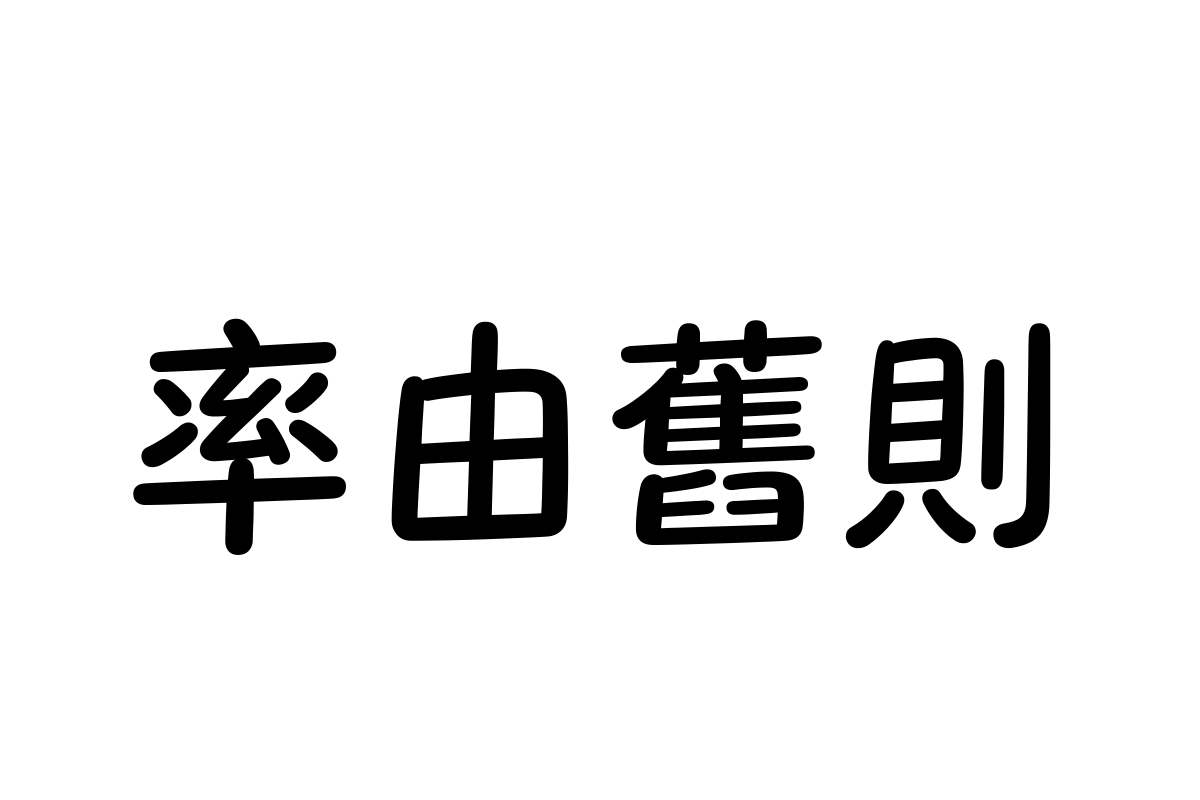
汉仪玛奇朵是一款具有现代感的中文字体,适用于各种设计项目,如广告、包装、网页和印刷品等。这款字体以其优雅的线条和独特的结构而闻名,能够为设计作品增添一份独特魅力。
汉仪玛奇朵采用简洁明了的设计,字形清晰易读,适合用于需要突出文字内容的设计场景。该字体的笔画流畅,给人一种轻盈的感觉,使得整体设计显得更加自然和谐。
此外,汉仪玛奇朵还具有多种字重选择,包括常规、粗体、斜体等,以满足不同设计需求。这些字重的选择也使得汉仪玛奇朵能够更好地适应不同的设计场景,无论是正式的商业报告还是轻松的日常交流,都能够轻松应对。
总的来说,汉仪玛奇朵是一款非常适合现代设计风格的中文字体,其优雅的线条和独特的结构使其在众多字体中脱颖而出,成为设计师们的首选之一。